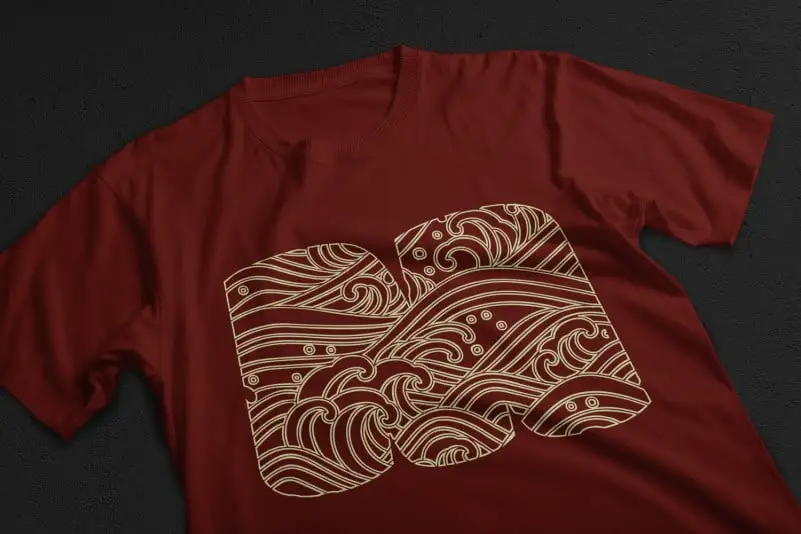
A fonte ‘OCEAN WAVE’ é inspirada na obra “Grande Onda no Mar de Kanagawa” de Katsushika Hokusai, uma pintura icônica que retrata a majestosa onda do Japão. Esta fonte decorative captura o poder e a vitalidade das ondas oceanicas em cada letra, oferecendo um visual vibrante e despojado ideal para aplicações digitais modernas. Inspirada no estilo japonês tradicional, esta fonte display é perfeita para gráficos envolventes que se destacam do resto da página. Com uma composição elegante que incorpora elementos decorativos e atraentes, ‘OCEAN WAVE’ tornará seu projeto mais intrigante. Este recurso gráfico oferece uma alternativa àtrica de estilos convencionais, permitindo que você enriqueça sua criação com um elemento visual único que se destaca na tela digital. Não importa a aplicação do seu design — seja em banners, logotipos ou até mesmo em designs de interface de usuário modernos, ‘OCEAN WAVE’ oferecerá o poder e a beleza da natureza marinha no centro de sua criação.